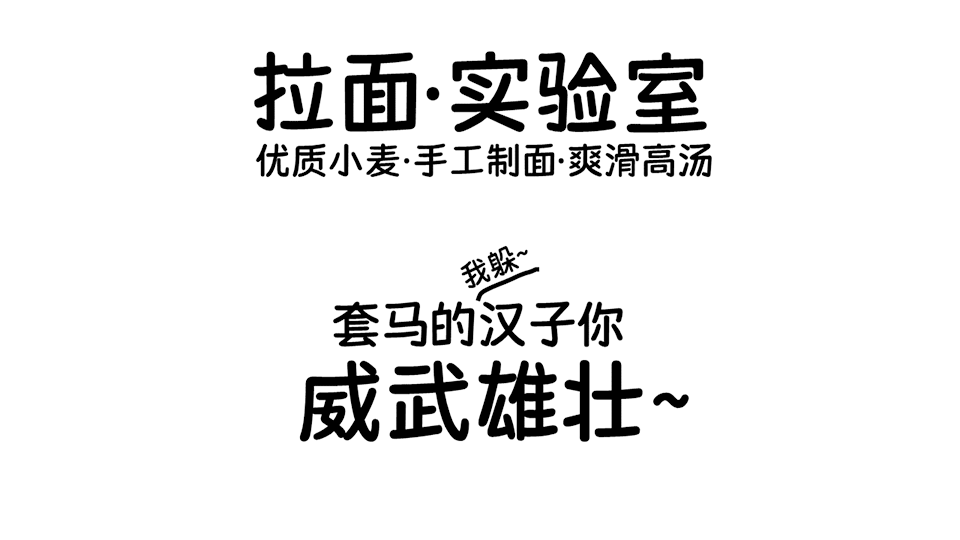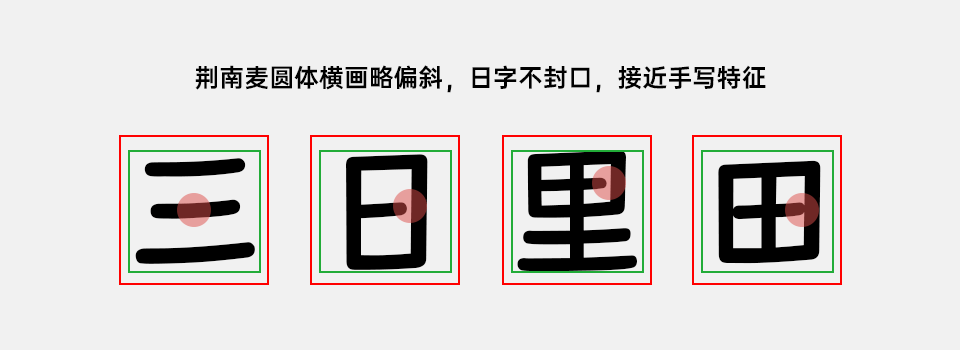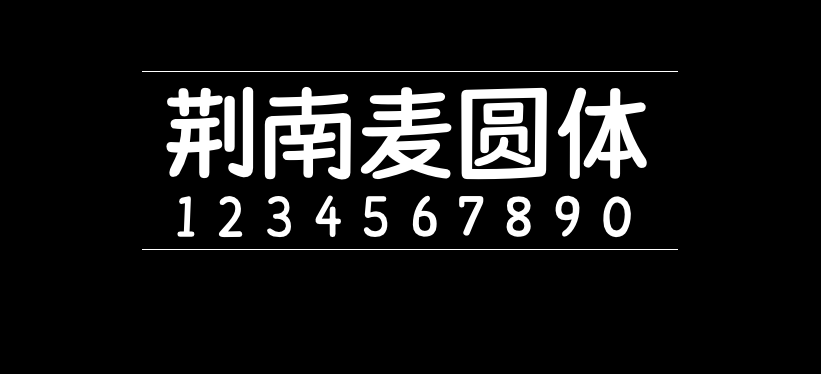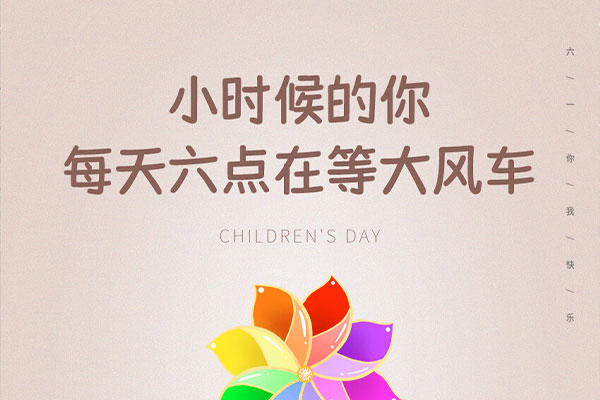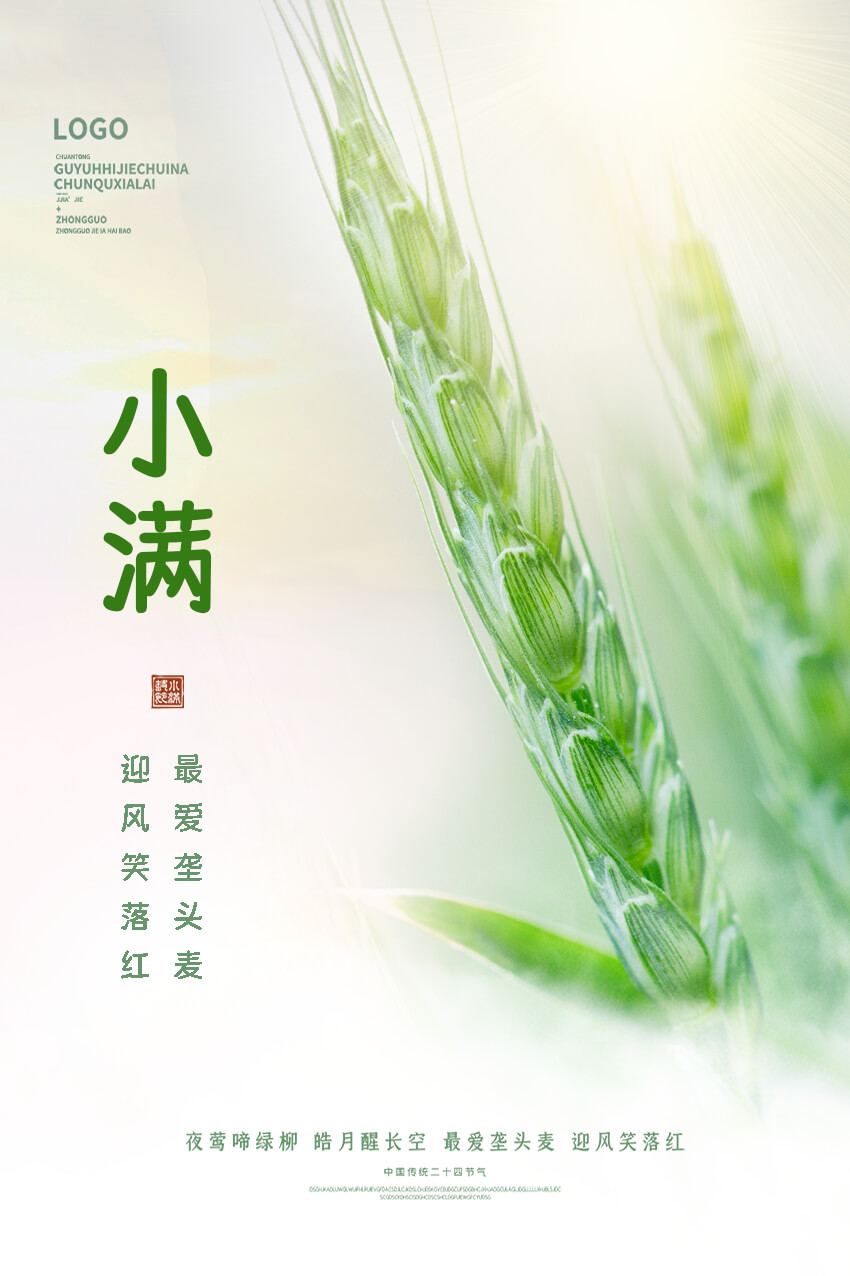
荆南麦圆体
荆南麦圆体是荆南字坊推出的第二款免费商用字体,第一款是荆南缘默体,不知道大家用的还顺手吗?
荆南麦圆体的设计灵感来源于韩国的一个综艺节目上的谚文字体,手写的风格圆润的笔画让这款字体看起来很可爱。
荆南麦圆体
荆南麦圆体萌系可爱的手写风格,字体每个笔画的粗细相同,两端圆润饱满,凸显可爱风格。虽是手写字体,笔画分明没有细小的连接,使字体更加清新俏皮。无论是做食品类还是母婴类,抑或是儿童类的设计都特别适合。
荆南麦圆体
横画略偏斜,日字不封口,接近手写特征尾端圆润,横竖均一,保留趣味性的同时可读性高,也能适应屏幕显示。